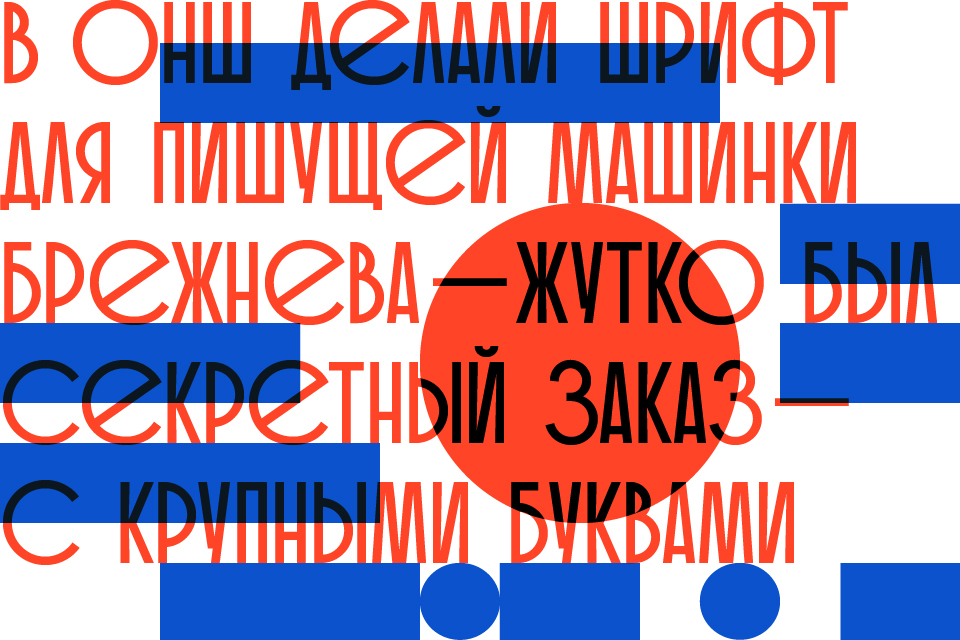
Oks typeface was initially based on letterforms popular in the USSR in 60's but in the course of time quite distanced from them.
Шрифт Oks создан на основе популярных в 60-е гг. буквенных форм (см., например, надписи на станциях метро «Таганская» и «Коломенская» московского метрополитена), но в своём развитии отошёл достаточно далеко от прототипа.
This rough and naive sans serif has certain charm and can be used in large sizes for headlines, posters, etc. The font contains only capitals.
Этот наивный, грубоватый геометрический гротеск во всей красе демонстрирует знаменитый «кириллический забор» и обладает определённым обаянием. Oks может применяться в кеглях от 36 и выше (можно и ниже, но тогда дайте ему разрядку). Содержит только прописные знаки.